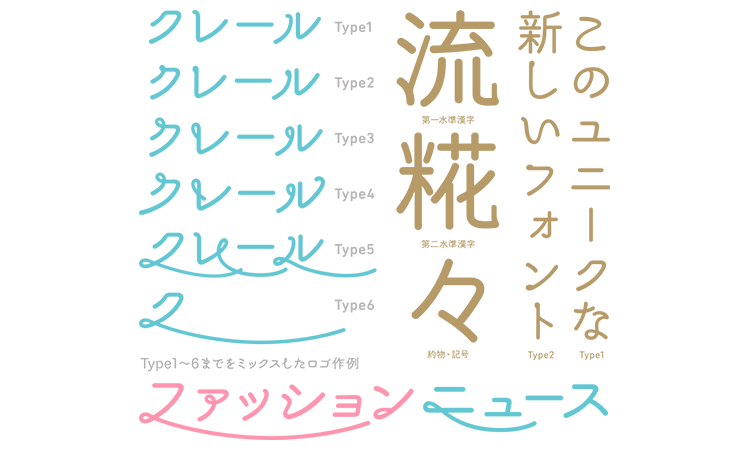
あさご本丸ゴシックは、クラシックな骨格の中に、ロマンチックな雰囲気のある丸ゴシック体のフォントです。恋人の聖地にも認定されている、天空の城、竹田城のある朝来市をイメージして作成されています。
伝統的な骨格をベースとしながら、クルクルとした曲線がロマンチックで、モダンな雰囲気を表現しています。個性的で遊び心がありながら、遊びすぎないオールドスタイルのフォントで、幅広い場面で使うことができます。のびのびとした線が、美しく、優しい世界観を作り出しています。
製品版のサンプル
フリーフォントの「あさご本丸ゴシックmini」と製品版の「あさご本丸ゴシック」があります。
製品版は、第一水準の漢字2965字と第二水準のよく使う漢字460字、記号類・約物・キリル文字・半角カタカナ等647字が含まれています。フリーフォントとは異なり、縦書きも可能になっています。また、TrueTypeも梱包されています。さらに、特典としてクルクルとしたカールの度合いが異なる6点のフォントが付属しています。それぞれに特徴があり、Type1はシンプル、Type2は個性的な先端、Type3は遊び心のあるデザイン、Type4は伸びやかで見出し向き、Type5はロゴの一部に使えそうなデザイン、Type6はType5の倍の横幅になっています。